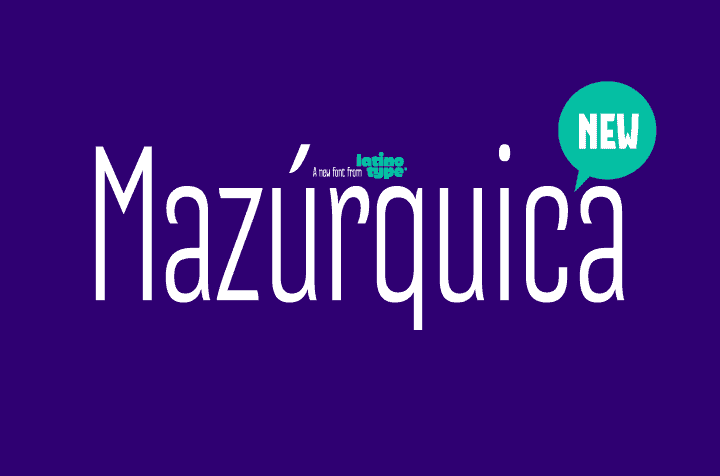
A Mazurquica é uma tipografia sans-serif que oferece uma sensação extra condensada, perfeita para títulos e headlines que buscam impacto e estilo. Com três pesos: Ligera (leve), Media (medio) e Pesada (pesado), esta fonte se adapta a diversos aplicativos, desde cartazes até materiais de divulgação em geral. Uma característica interessante é sua coleção de ligaduras nas letras maiúsculas, que dão ao texto uma aparência única e distintiva. Esta fonte é excelente para utilização em publicações como revistas, livros e material promocional, incluindo cartazes, folders, panfletos e outros materiais. A Mazurquica traz consigo a versatilidade necessária para qualquer projeto que precise de um visual moderno e impactante, tornando-se uma escolha inteligente para designers em busca de uma tipografia única e eficaz.